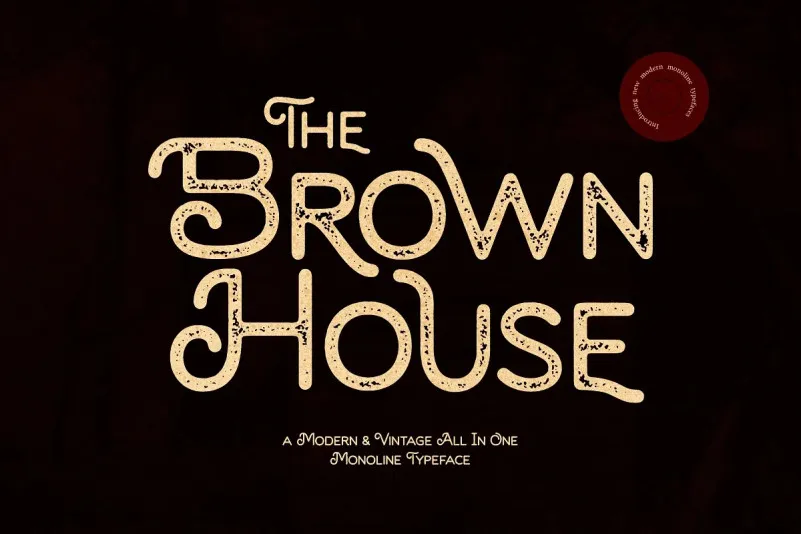
A fonte Brown House é uma opção perfeita para aqueles que buscam dar destaque a títulos curtos num design retro e elegante. Especialmente projetada para nomes de empresa, cartazes publicitários ou até mesmo capas de livros, essa fonte é um acréscimo encantador ao seu trabalho. Com três estilos principais – Regular, Rough e Stamp – e uma variedade única de ornamentos que permitem personalizar ainda mais o design, esta fonte lembra os movimentos artísticos decorativos e arquitetônicos do passado. Ela é composta por uma versão alternativa com gílios especiais para um toque extra de originalidade. Brown House não apenas oferece multilíngue para atender a todas as necessidades linguísticas, mas também inclui um conjunto alternativo que permite adaptá-la a qualquer tipo de aplicação. Com essa fonte em sua coleção, você poderá dar uma aparência vintage perfeita à sua obra, garantindo que ela seja tanto reconhecível quanto charmosa. Com esse design versátil e vibrante, Brown House não apenas é uma opção elegante para seus trabalhos gráficos, mas também uma fonte ideal para aqueles buscando dar um toque único a suas criações.